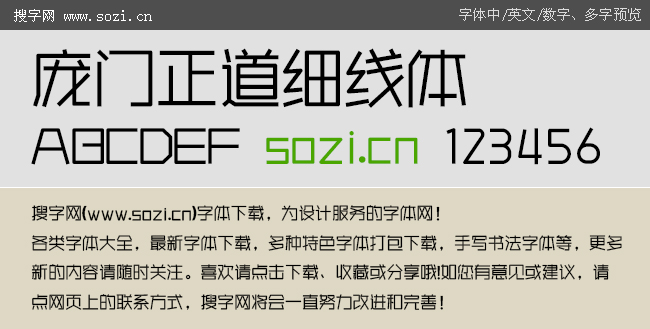
龐門(mén)正道細(xì)線(xiàn)體
搜字網(wǎng)給大家提供一款龐門(mén)正道細(xì)線(xiàn)體中文字體下載,龐門(mén)正道細(xì)線(xiàn)體字型方正。 接近正方形,中宮大,結(jié)構(gòu)均勻。字面比例約占90%,默認(rèn)字距設(shè)置合理,閱讀舒適。龐門(mén)正道細(xì)線(xiàn)體中遇到筆畫(huà)特別密集的,會(huì)保留主筆畫(huà)灰度,保證反均習(xí)統(tǒng)一,不影響字體識(shí)別度。適合應(yīng)用于藝術(shù)設(shè)計(jì)、平面宣傳設(shè)計(jì)、網(wǎng)頁(yè)設(shè)計(jì)等廣告設(shè)計(jì)。